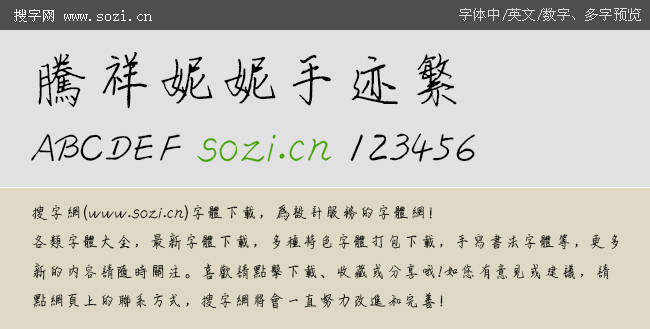
騰祥妮妮手跡繁
搜字網(wǎng)提供一款騰祥妮妮手跡繁中文藝術(shù)字體下載,騰祥妮妮手跡繁是一款很漂亮的手寫字體,書寫風格自然流暢,獨具風格,稚拙中透顯出活潑靈動的氣息;無雕琢,無拘束質(zhì)樸的視覺效果,用于正文更體現(xiàn)出手寫自然之感。字體可以廣泛應用于印刷出版、包裝設計、廣告設計、網(wǎng)頁設計等領域。